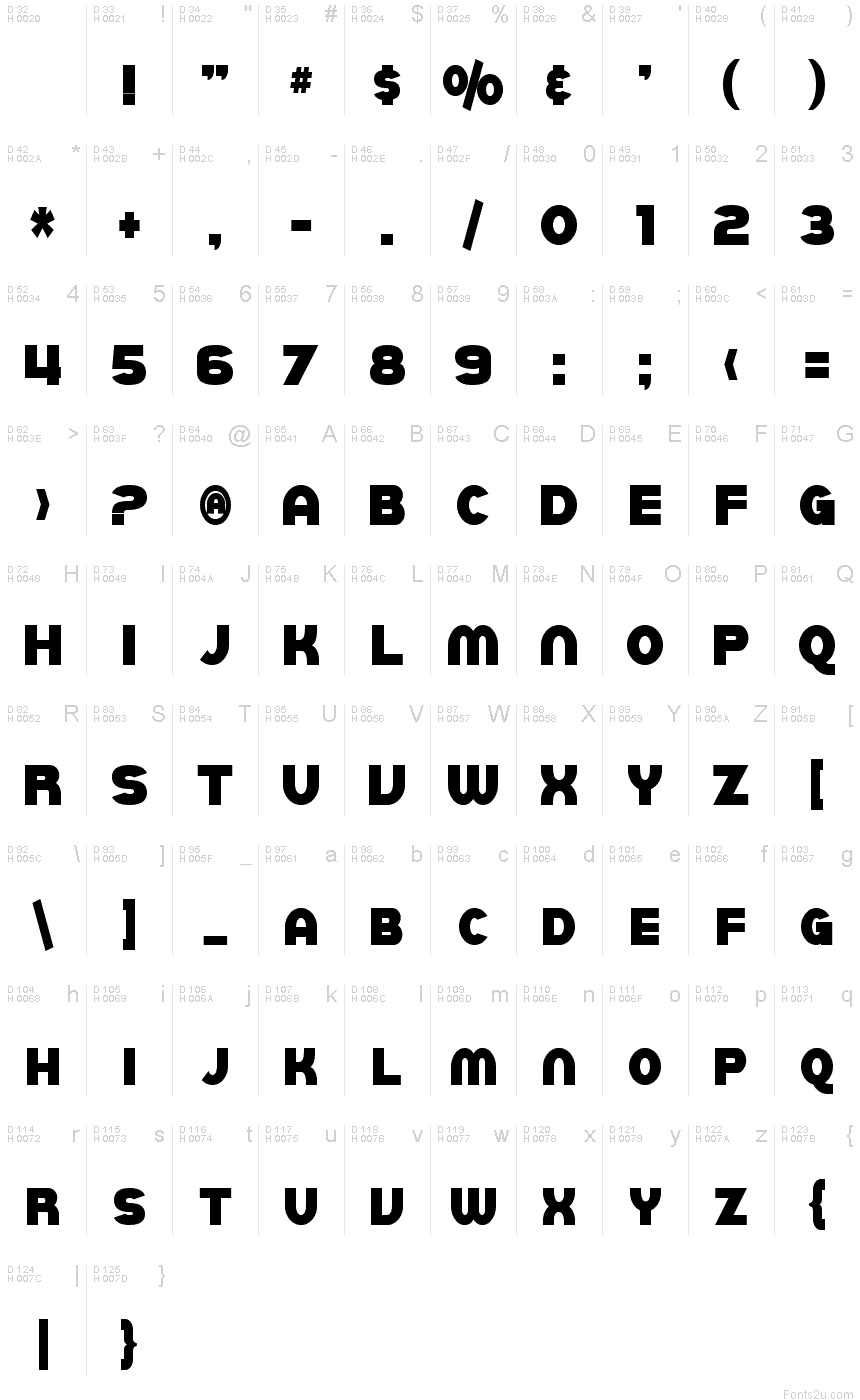
SF Juggernaut Condensed Bold od ShyFoundry to bezpłatny, nowoczesny krój pisma typu display, składający się wyłącznie z wielkich liter. Ma ciężki, zdecydowany rytm i wyraziste, zaokrąglone cięcia, dzięki którym litery wydają się zwarte i pełne energii. Połączenie płaskiej geometrii z głębokimi, zakrzywionymi wcięciami nadaje krojowi kompaktowy, industrialny charakter, który przywodzi na myśl zarówno styl retro, jak i branding sportowy.
Świetnie sprawdza się na okładkach albumów, plakatach wydarzeń, grafikach streetwearowych, w tytułach i krótkich hasłach, gdzie kilka liter musi mieć naprawdę mocny przekaz. Jako darmowy font, doskonale nadaje się też do monogramów i szkiców logo, ponieważ ciasna budowa i przerysowane krzywizny nadają nawet bardzo krótkim słowom solidną, blokową formę.
SF Juggernaut Condensed
ShyFoundry
Derek Vogelpohl